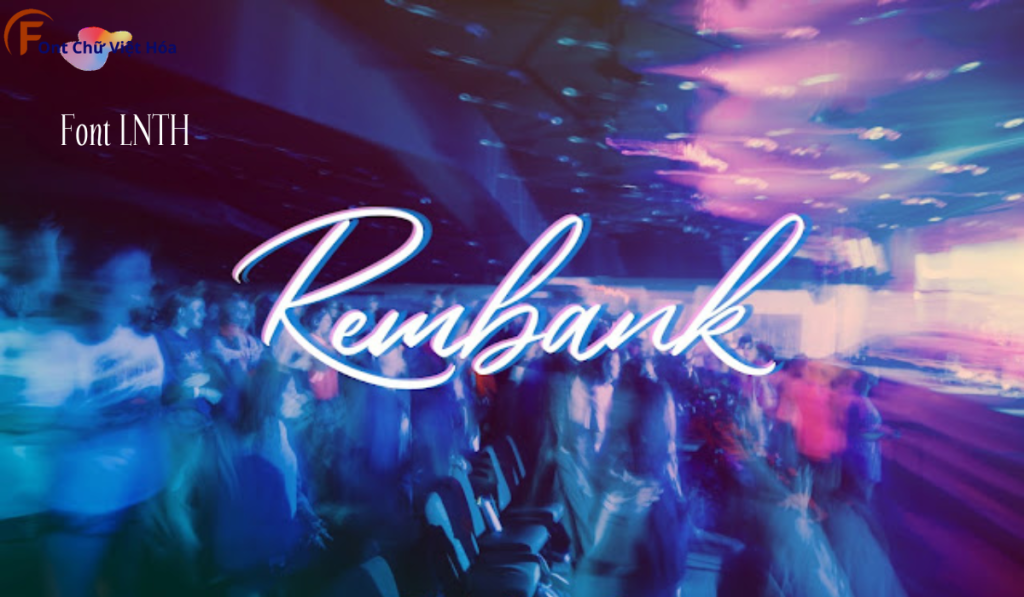
Font LNTH Rembank Việt Hóa
Font LNTH Rembank Việt Hóa là một font chữ hiện đại, thuộc bộ LNTH, với thiết kế đơn giản và tinh tế. Phong cách của font này phù hợp với các dự án thiết kế cần sự hiện đại và thanh lịch, như logo, tiêu đề, hoặc bảng hiệu. Font LNTH Rembank Việt Hóa mang đến sự hiện đại và dễ nhận diện, ứng dụng trong các lĩnh vực sáng tạo. Đặc điểm hình dạng của font bao gồm các đường nét gọn gàng và tinh tế, giúp tăng tính thẩm mỹ và sự chú ý. Việc Việt hóa font giúp người dùng dễ dàng sử dụng trong các thiết kế tiếng Việt, mang lại sự tiện lợi và linh hoạt.